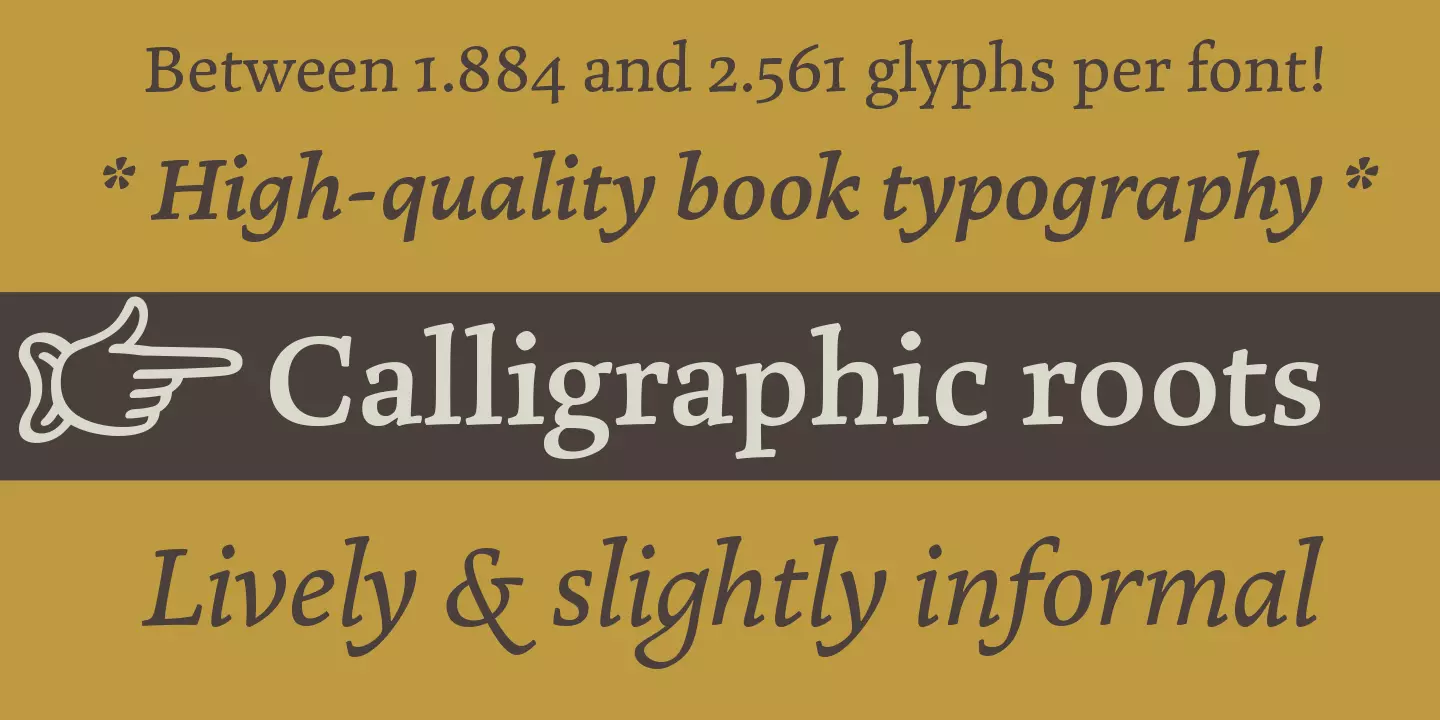
Schrift für Jugendbuch mit kalligrafischer Note gesucht
ich suche für ein Jugendbuch eine freundliche und sehr gut lesbare Textschrift mit einer kalligrafischen Note, da es um ein Tagebuch geht.
Die Nassim ist mir hier untergekommen, ist mir aber zu ernst/erwachsen/orientalisch.
Fällt euch was Schickes ein?
Es wäre zugegebenermaßen recht unorthodox, aber könnte man sich vorstellen, ein komplettes Buch kursiv zu setzen?
Das hatte ich ehrlich gesagt auch schon überlegt, aber ich glaube, das wäre zu heavy.
Ich habe die Schrift nicht, daher kann ich ihre Qualität für lange Texte beurteilen, aber ich hab mir irgendwie in die Erinnerung gepackt für "hat mit Minderjährigen zu tun": https://www.myfonts.com/fonts/ascender/ayita-pro
Scheint zu passen, denn meine beiden Kinder (12 und 13) standen gerade beim Aufruf der verlinkten Seite hinter mir und fanden die Schrift ziemlich klasse.
Ist schon viele Jahre her, aber ich habe mal einen Krimi gelesen, gesetzt in der Minion Pro, bei dem jedes zweite Kapitel ein Monolog war. Um das typografisch deutlich zu machen waren diese kürzeren Kapitel komplett kursiv gesetzt. Ich muß sagen: damals fand ich das wirklich total unglücklich zu lesen, gerade im direkten Vergleich zu den "normalen" Kapiteln. Aus dieser Erfahrung hat sich bei mir eingebrannt, daß  lange kursive Texte schlechter zu lesen sind ...
Da die meisten Kursiven enger laufen, würde ich das auch erstmal nicht machen. Aber wenn man eine schöne lesbare Kursive zur Hand hätte und dazu noch irgendwie avantgardistisch drauf wäre … 😬
Ich muss sagen, dass die gerade mein Favorit ist! Passt gut zum illustrativen Cover, hat was mädchenhaftes, was gut zum Inhalt passt und sieht kursiv recht kalligrafisch aus.